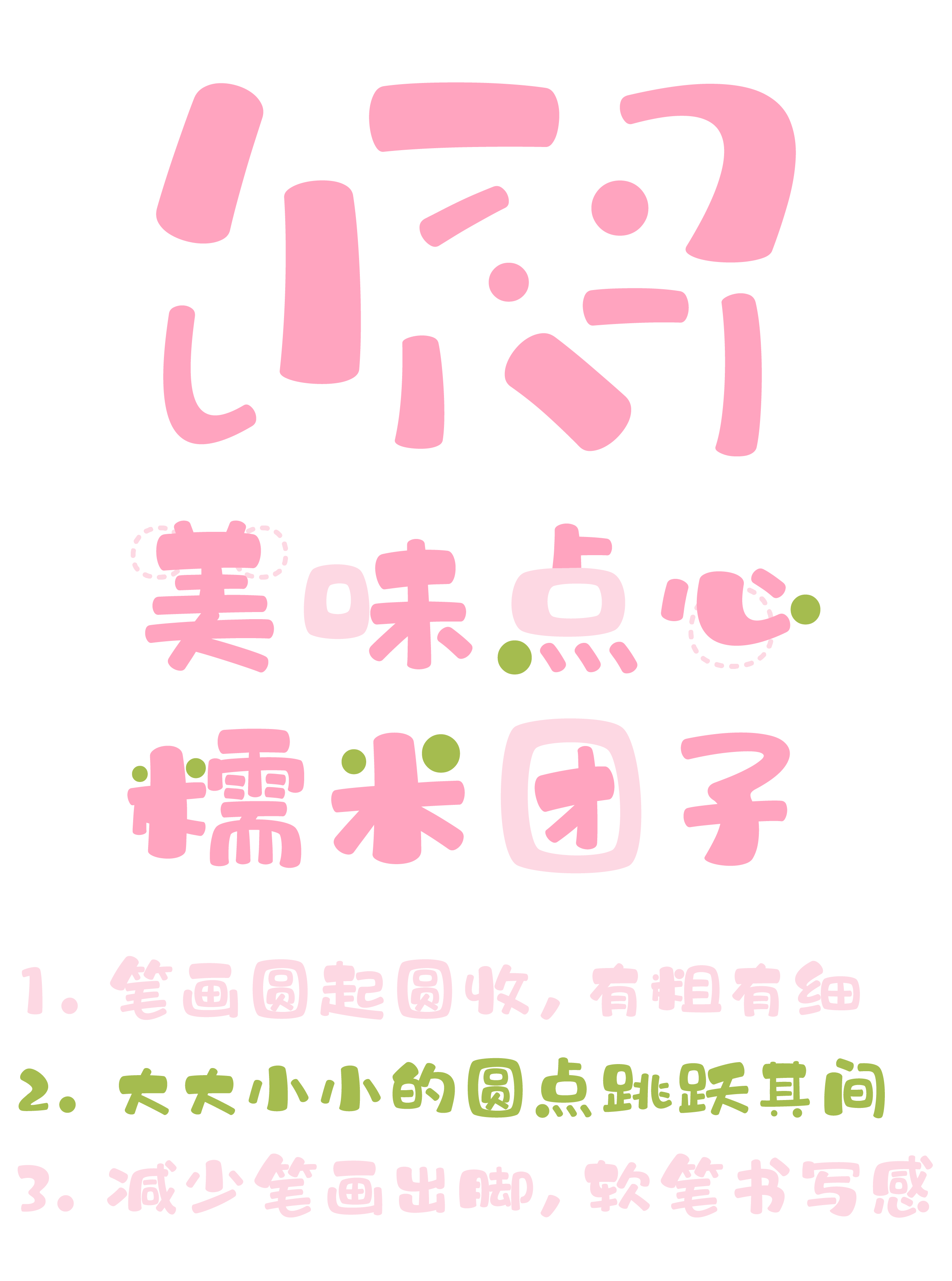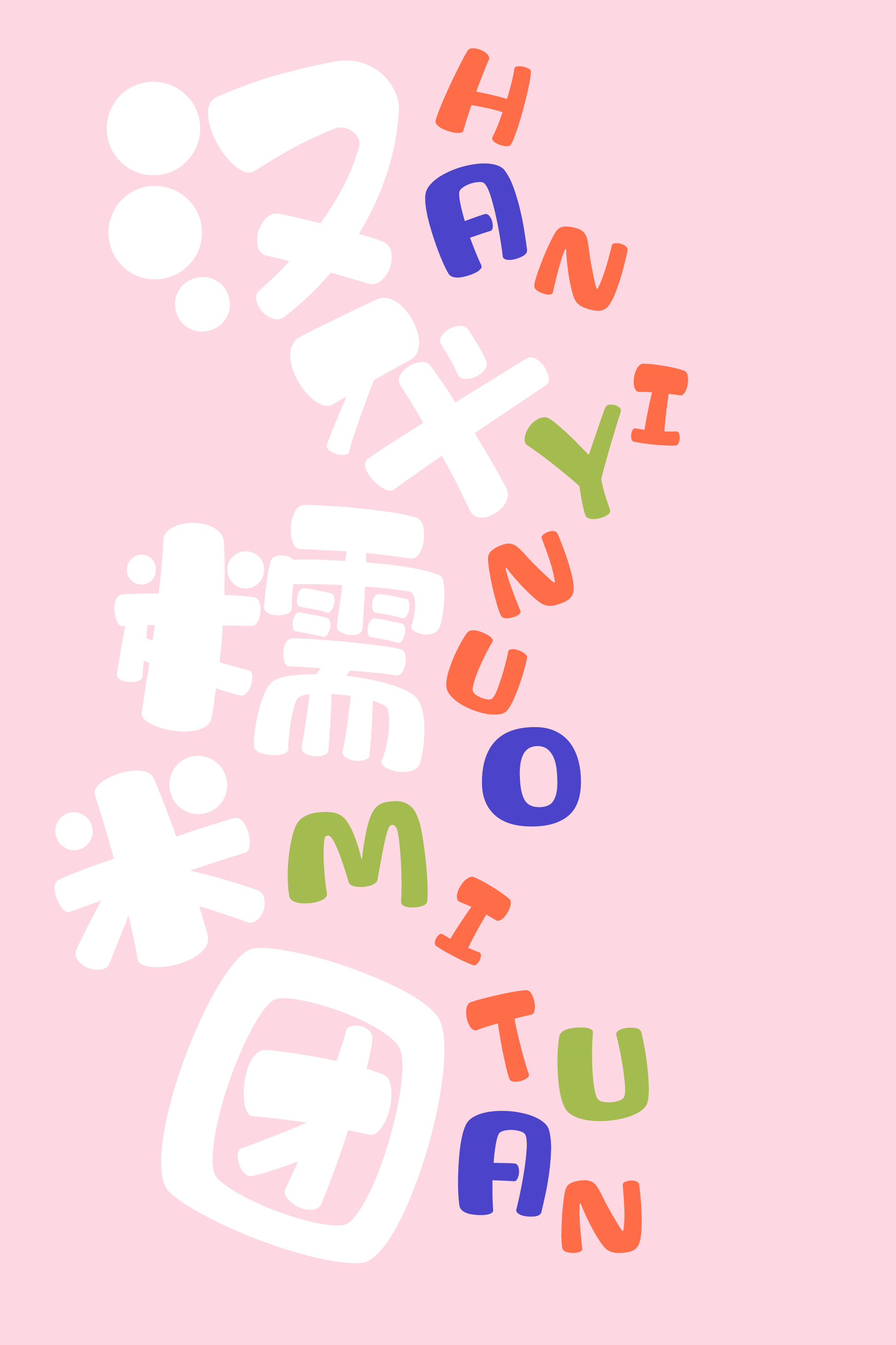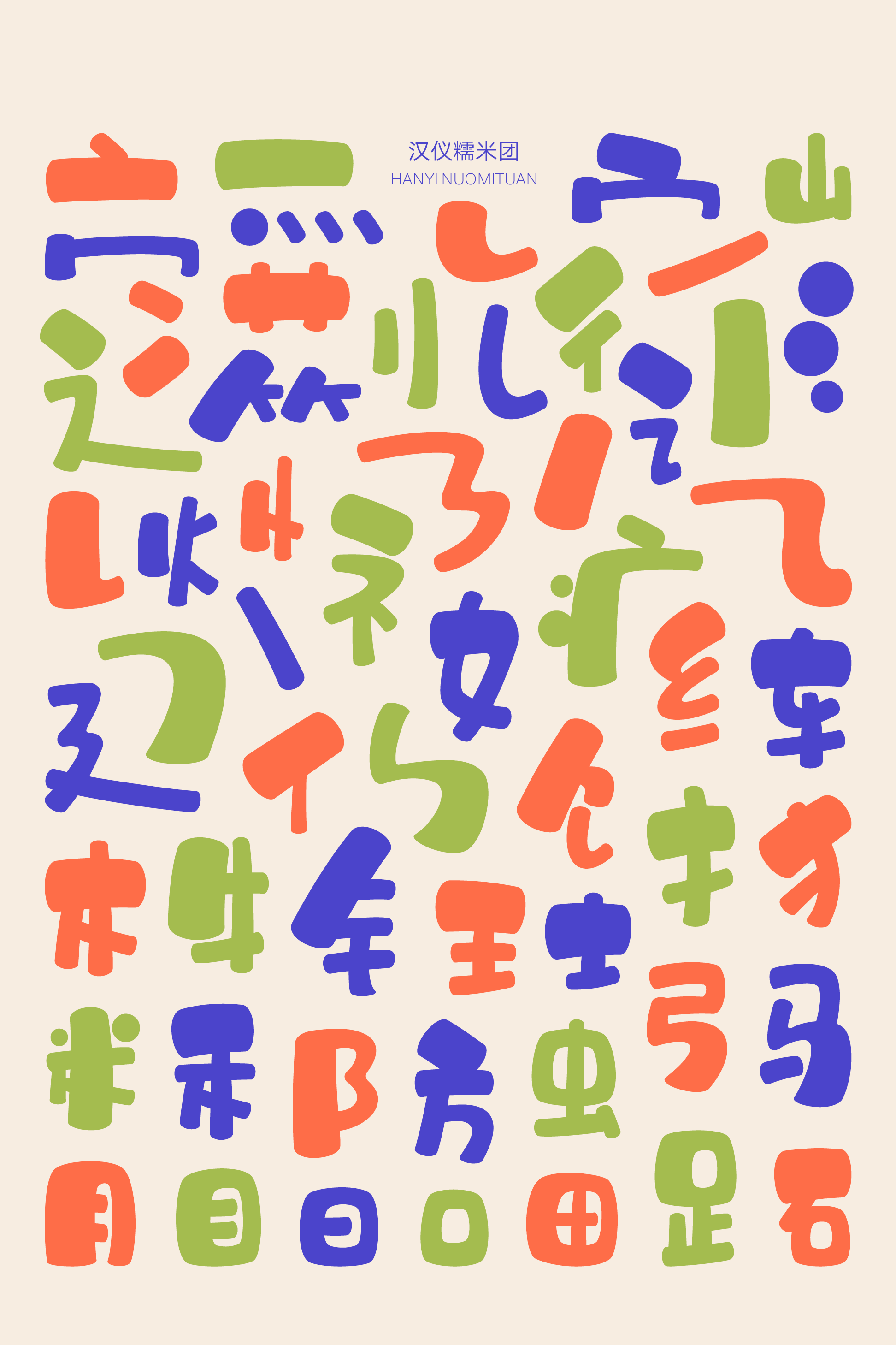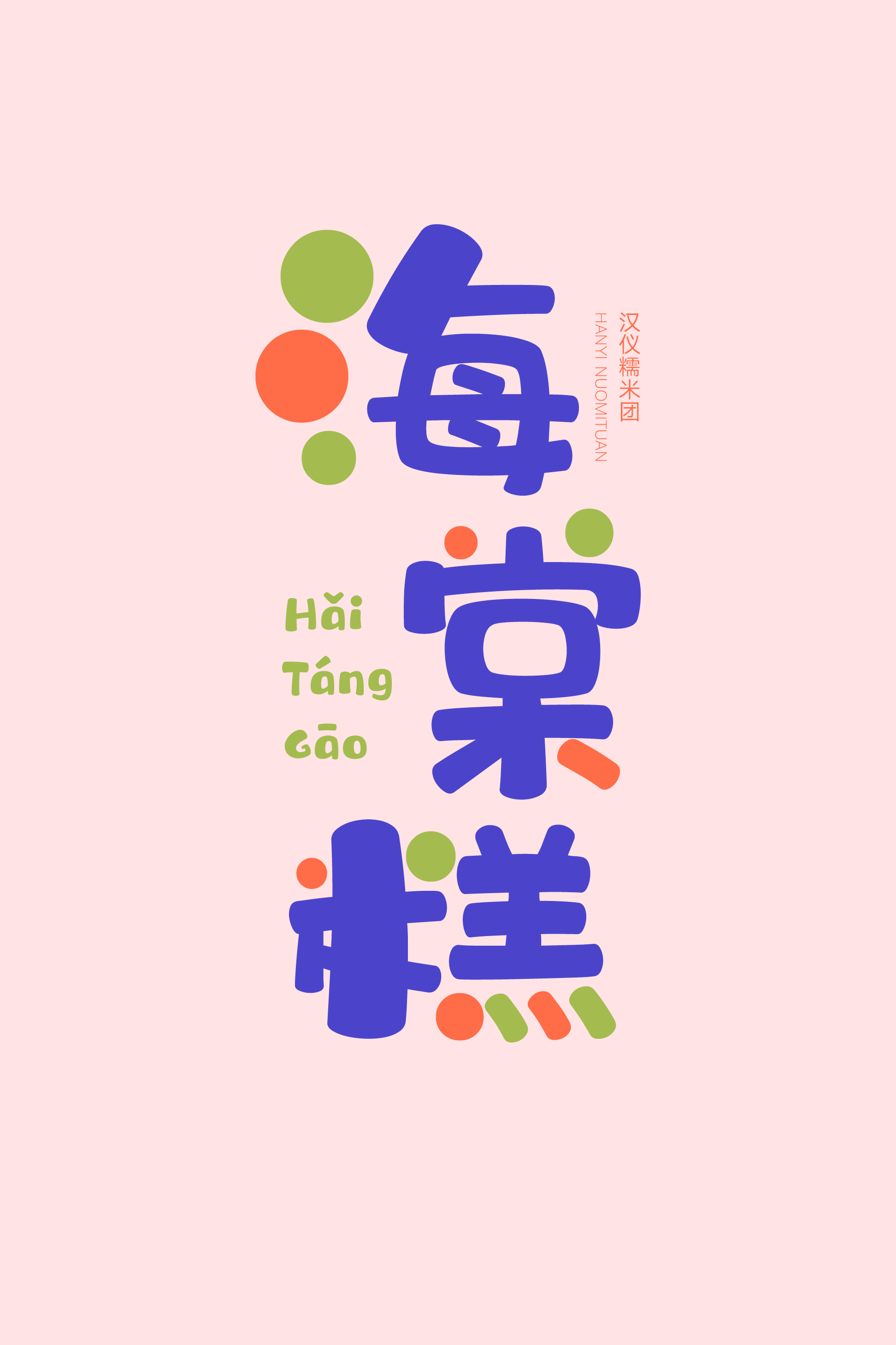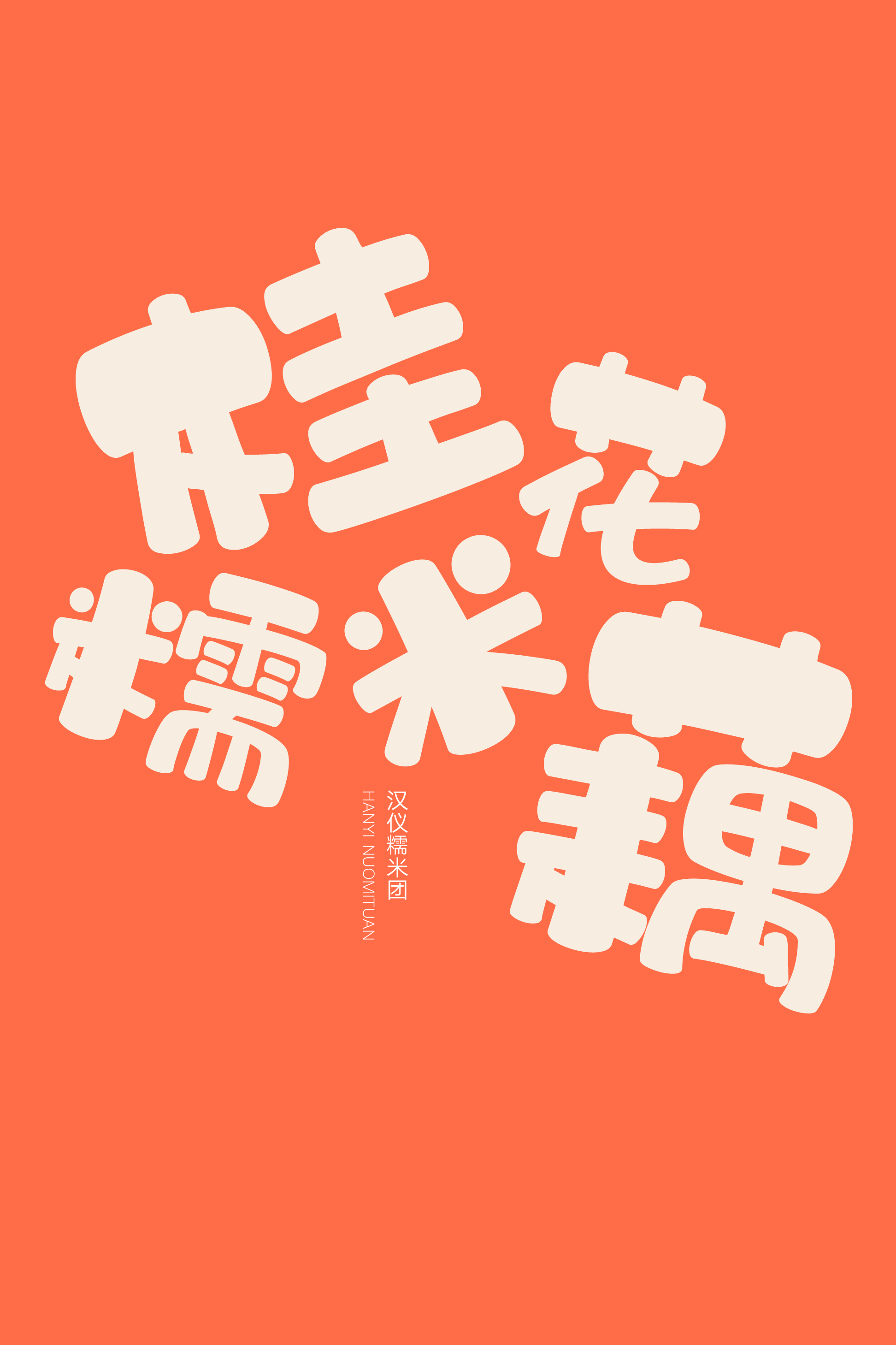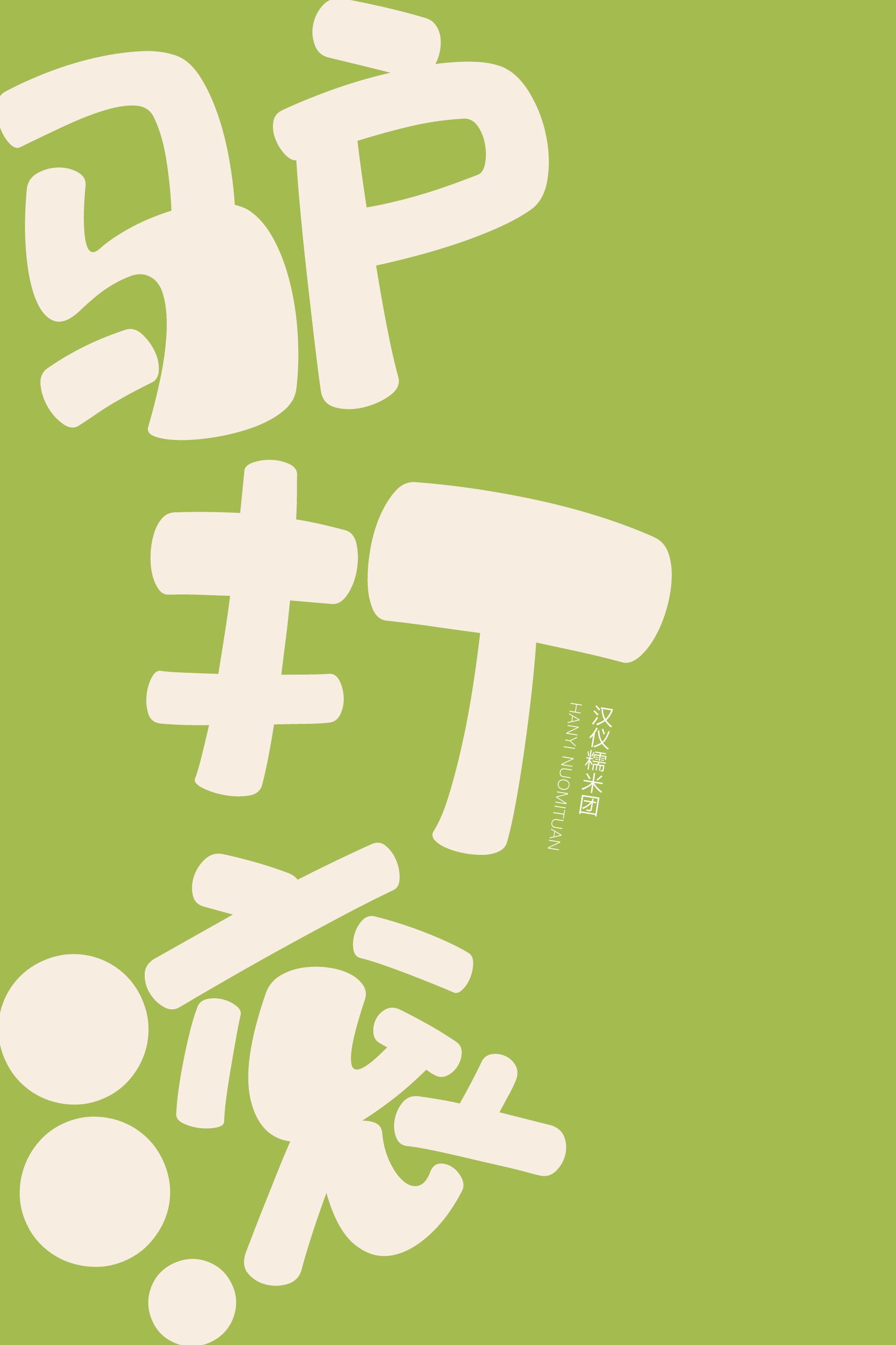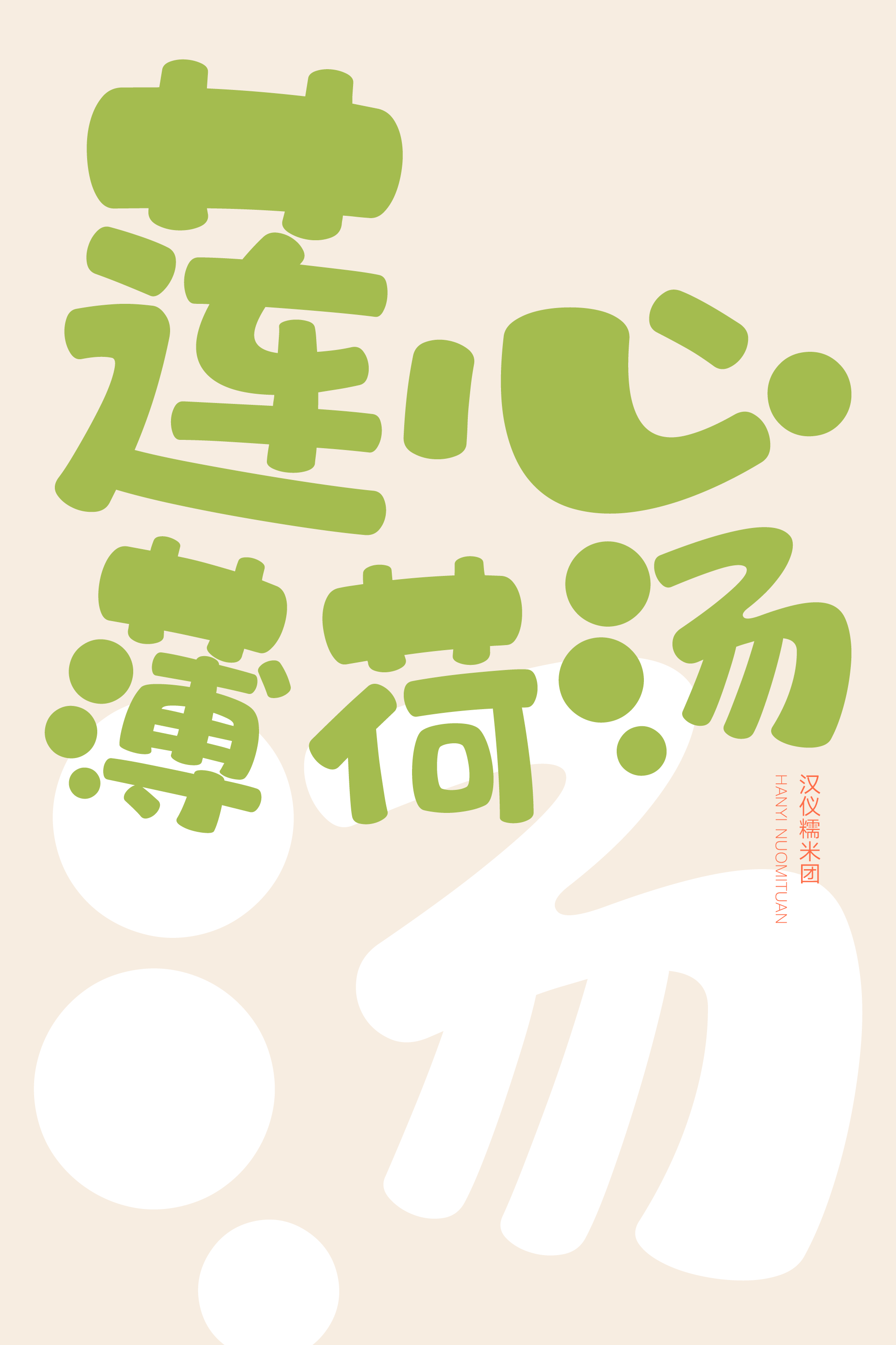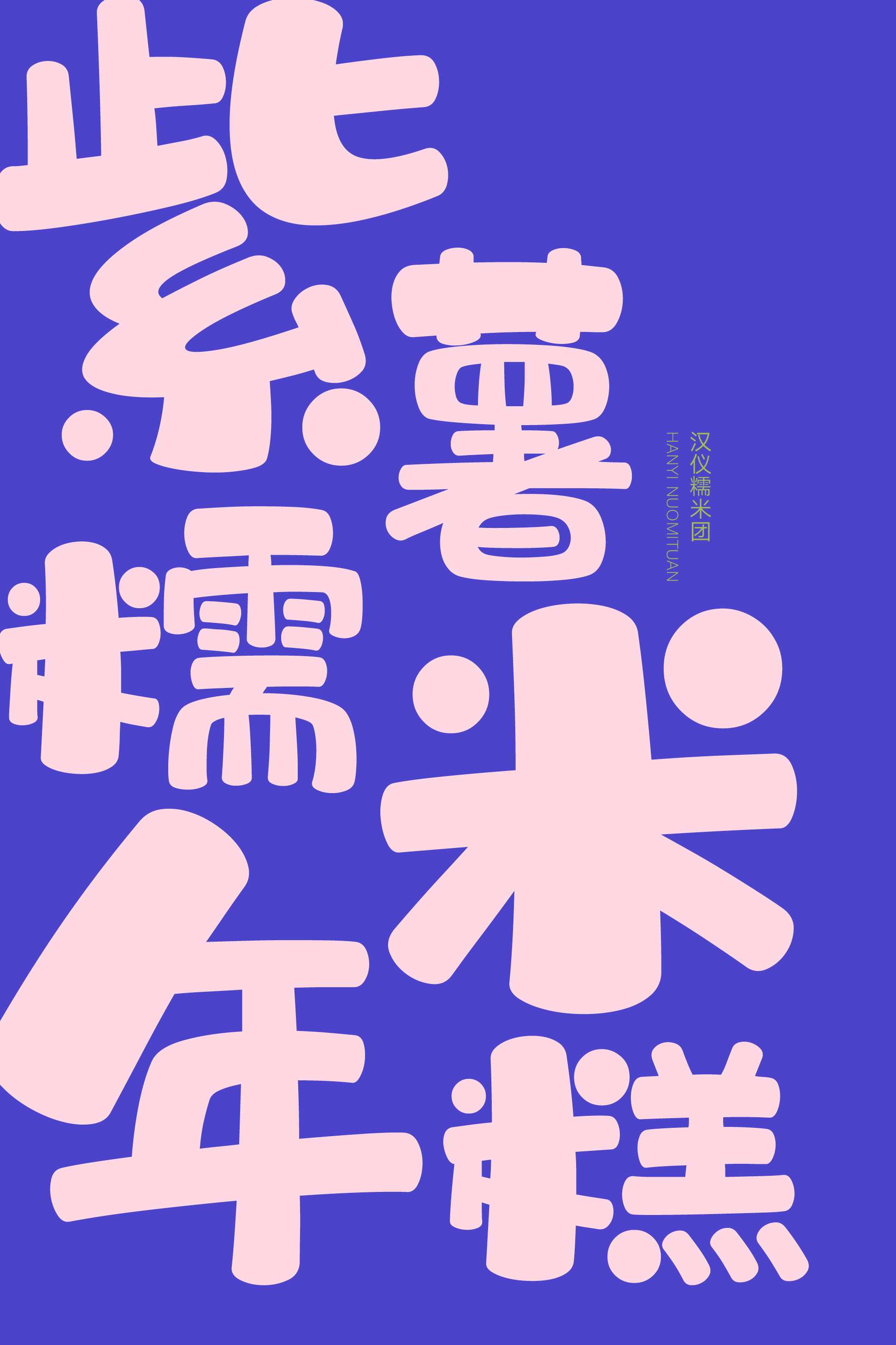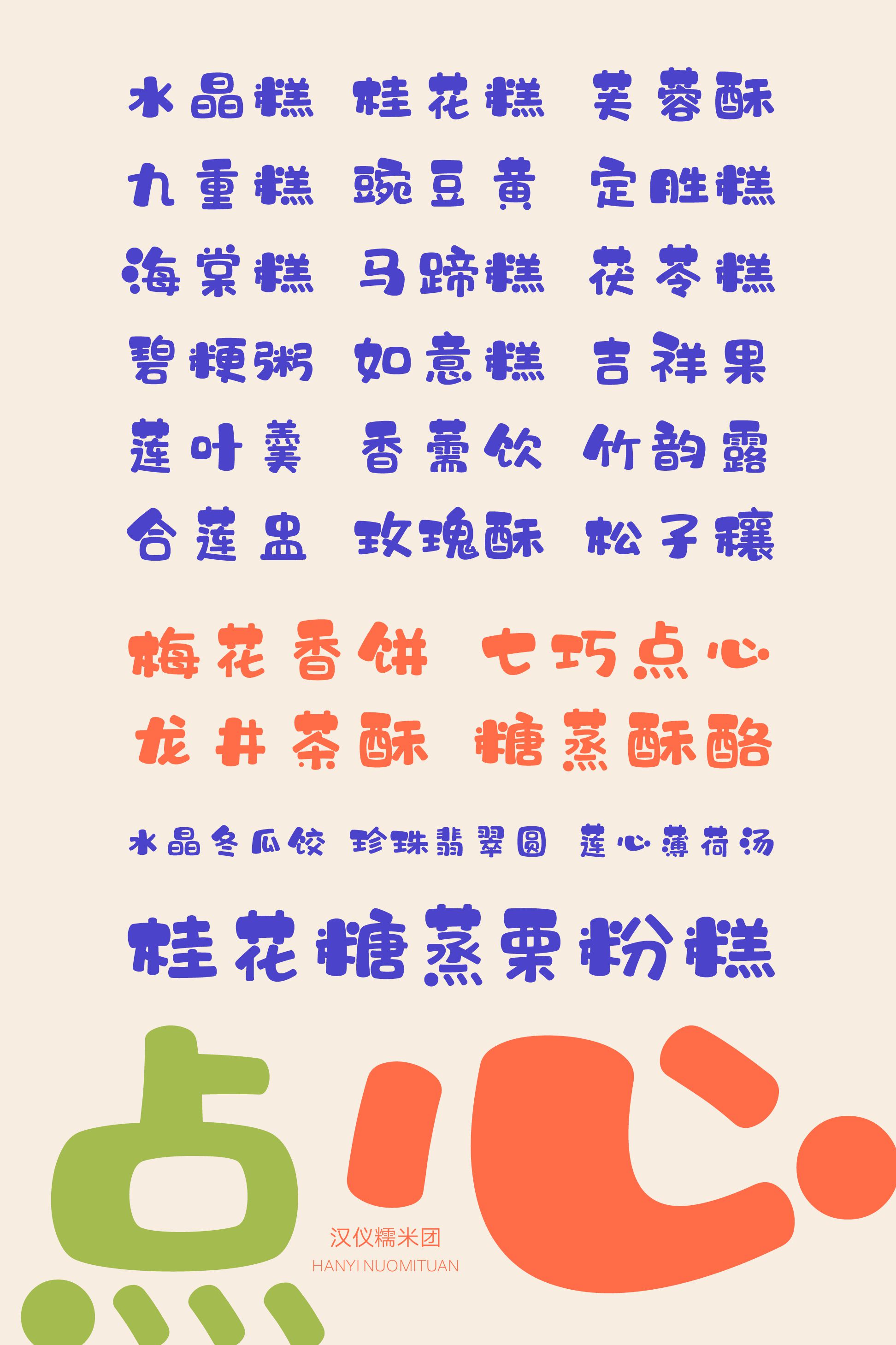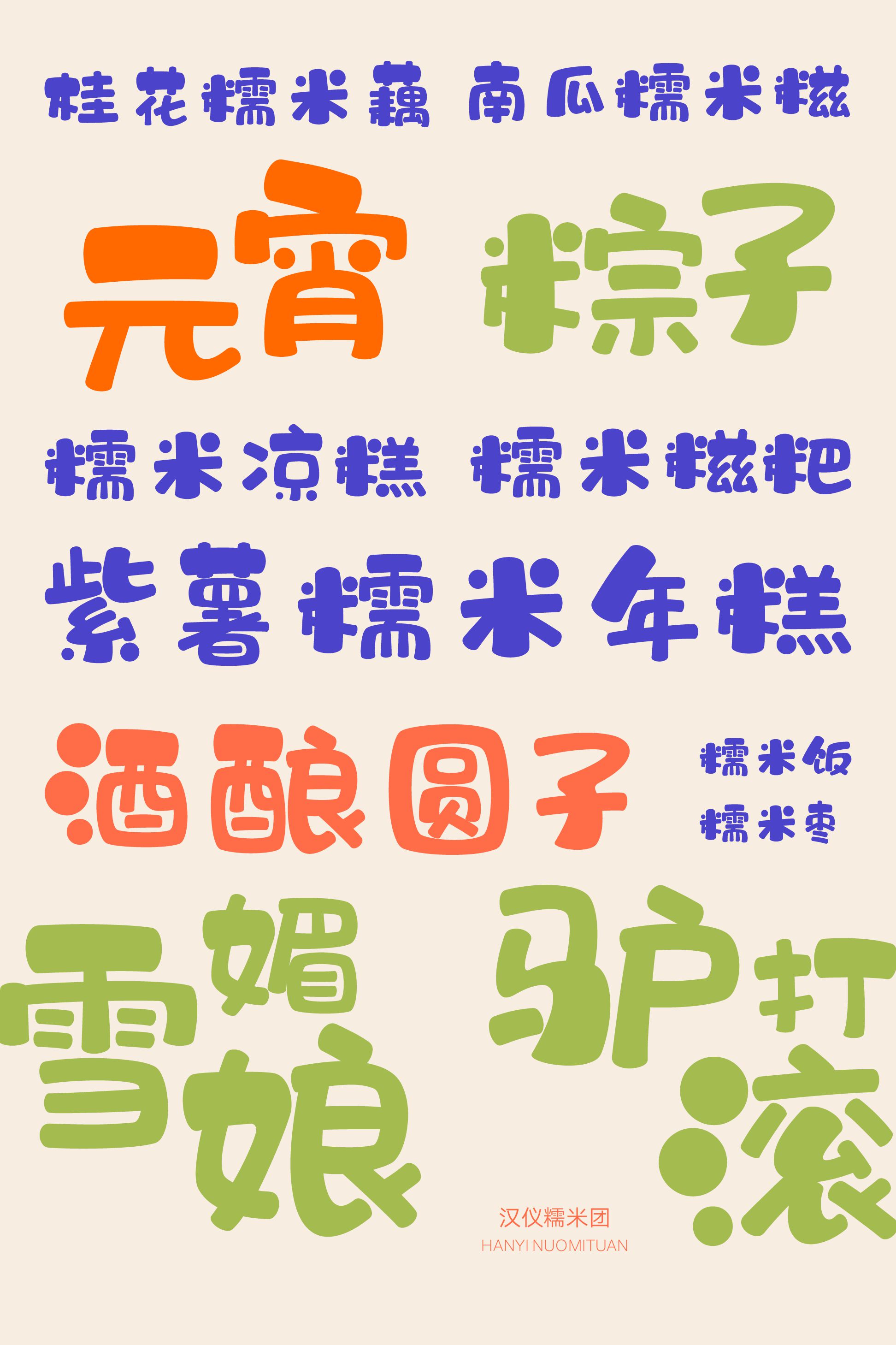
汉仪糯米团
圆滚滚软乎乎的汉仪糯米团,让人忍不住想咬一口。扁扁圆圆的字形、软糯饱满的笔画,看起来柔软而有弹性,结构舒朗放松,笔形简约圆润,圆点跳跃其间,有谁能拒绝这么可爱的糯米团呢?
趣味满满的汉仪糯米团是一款带有手写感觉的标题字体,既适用于甜点零食的包装,也可以应用于儿童玩具绘本,兼顾识别度和趣味性,小小的糯米团有着大大的能量。
字形扁扁圆圆像糯米团,大大小小,错落可爱。
结构舒朗放松,中宫较大。
笔画软糯饱满,柔软而有弹性。
西文部分同样是糯米团一样圆润饱满,笔画柔软有弹性。中西文搭配使用可以收获双倍的软糯美味。